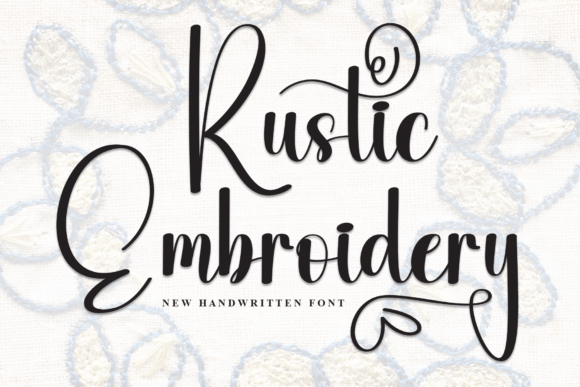
Rustic Embroidery
การค้นหาองค์ประกอบการออกแบบที่เหมาะสมอาจเป็นเรื่องท้าทาย แต่ Rustic Embroidery นำเสนอคอลเลกชันที่โดดเด่นซึ่งช่วยยกระดับงานของคุณได้ทันที
ไม่ว่าคุณจะสร้างผลิตภัณฑ์ POD (Print on Demand) คำเชิญงานแต่งงาน หรือกราฟิกโซเชียลมีเดีย Rustic Embroidery ก็เหมาะสมอย่างยิ่ง